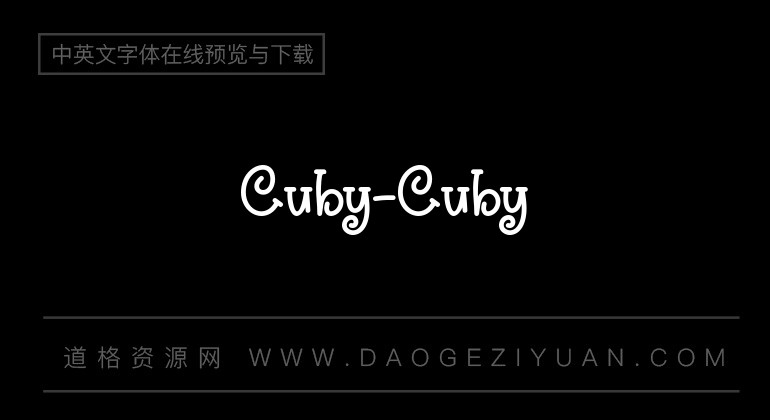
Cuby-Cuby 字体是一款拥有独特曲线和视觉效果的手写字体。它具有柔和、温暖的感觉,适合在报纸、杂志、网站等多种媒介上使用。它的设计风格富有古典气息,能够为文字添加温暖的气息,同时也能够突出文字的主题性。Cuby-Cuby 字体的特点是有着大胆的笔画,它的曲线更加流畅,拥有更好的视觉效果,能够营造出更加有趣的文字氛围。内容介绍
Cuby-Cuby是一款非常不错的手写艺术字体,具有很好的视觉感,适合于文化类的宣传设计、商业类品牌的广告和产品包装设计以及个性化文字排版等较多场景。